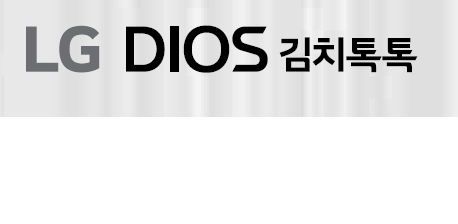
글씨체 알려주세요 kan*** 2023.02.03 DIOS 글씨체와 김치톡톡 글씨체 정보를 알고싶습니다. 끝에가 사선으로 잘리는 글씨체인데 전혀비슷한걸 찾을 수가 없어요 댓글 0 등록 쉽고 빠르게 가장 비슷한 폰트를 알고 싶다면? 이미지로 검색하기
김치톡톡 글씨체 정보를 알고싶습니다.
끝에가 사선으로 잘리는 글씨체인데
전혀비슷한걸 찾을 수가 없어요